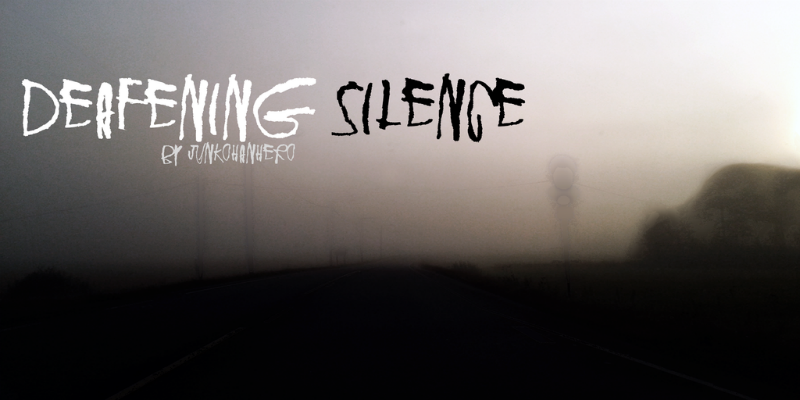
Deafening Silence font
Aqui está uma descrição envolvente e natural para a página de download da font ‘Deafening Silence’, focada nas características do design e no designer: Descobrimos uma nova fonte chamada Deafening Silence, que não apenas preenche sua necessidade de uma mistura única e vibrante de estilos, mas também promete trazer seu projeto à vida com um som dramático. Ideal para qualquer tipo de projeto em display, como banners ou identidades visuais, essa elegante fonte é perfeita para projetos que exigem destaque visual. Criada pelo designer Hamilton, Deafening Silence oferece uma combinação única de linhas suaves e formas marcantes, criando um resultado que não apenas chama a atenção do seu público-alvo, mas também ressoa com o coração de quem está olhando. Seu uso pode ser tanto no seu site quanto em sua marca impressa ou até mesmo na sua campanha publicitária. Se você estiver interessado em personalizar mais ainda suas criações, Hamilton tem um serviço para o mercado comercial disponível. Para adquirir a versão com licença de propriedade intelectual do Deafening Silence font, basta entrar em contato por meio de uma simples transação no PayPal e enviando sua mensagem, você pode começar a utilizar essa poderosa ferramenta imediatamente. Com o Deafening Silence, Hamilton não apenas entrega um produto excepcional; também promete oferecer suporte ao cliente para ajudá-lo a maximizar todo o potencial de sua nova font. Seja para seu próximo projeto ou para manter seu design atualizado e vibrante com as últimas tendências, você certamente encontrará muitas maneiras de explorar completamente essa maravilhosa novidade.